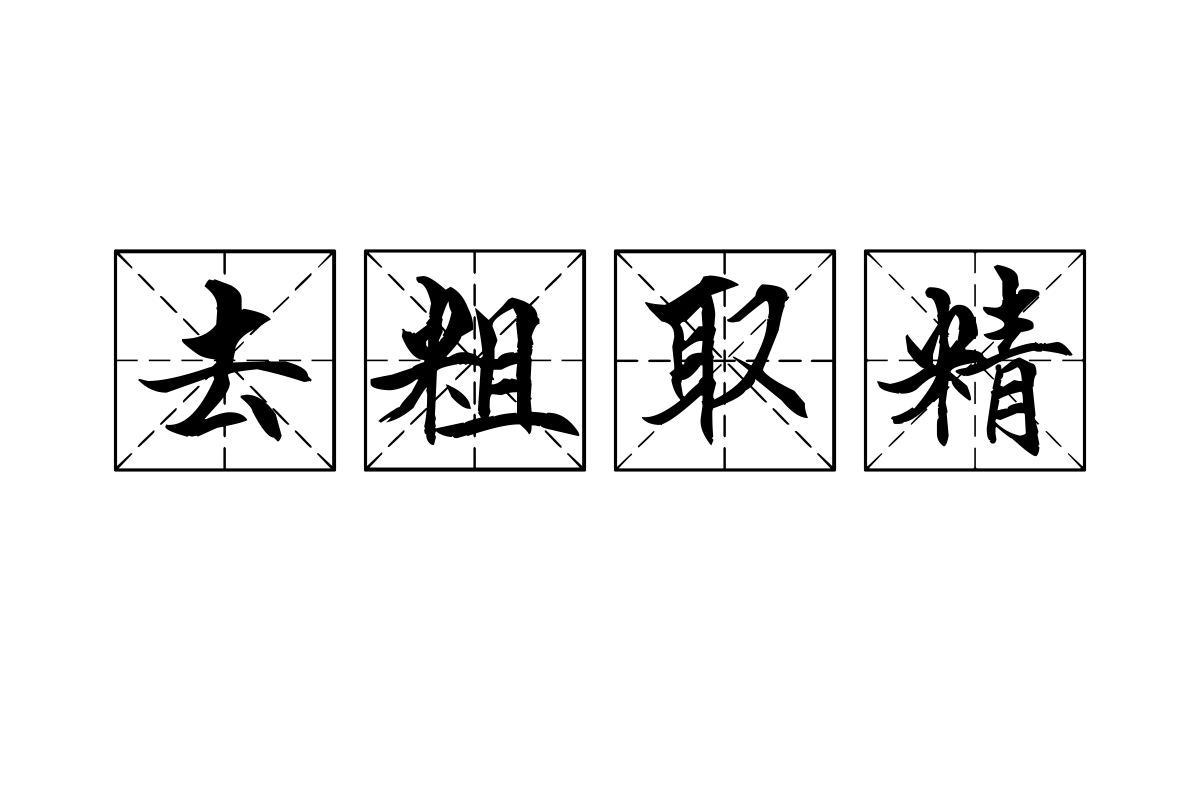
汉标串城米格体字体是一款具有独特风格的中文字体,它采用了现代的设计手法和结构,使得字体看起来更加时尚、动感。这款字体的特点在于其笔画流畅,字形紧凑,给人一种简洁而有力的感觉。
汉标串城米格体字体的线条粗细适中,既不会过于粗犷,也不会过于细腻,这使得它在印刷和显示设备上都能保持良好的可读性。此外,这款字体还具有一定的装饰性,可以在一些需要强调的地方使用,以达到更好的视觉效果。
总的来说,汉标串城米格体字体是一款适合用于各种商业和设计场合的字体,无论是在网页设计、平面设计还是包装设计中,都能展现出其独特的魅力。